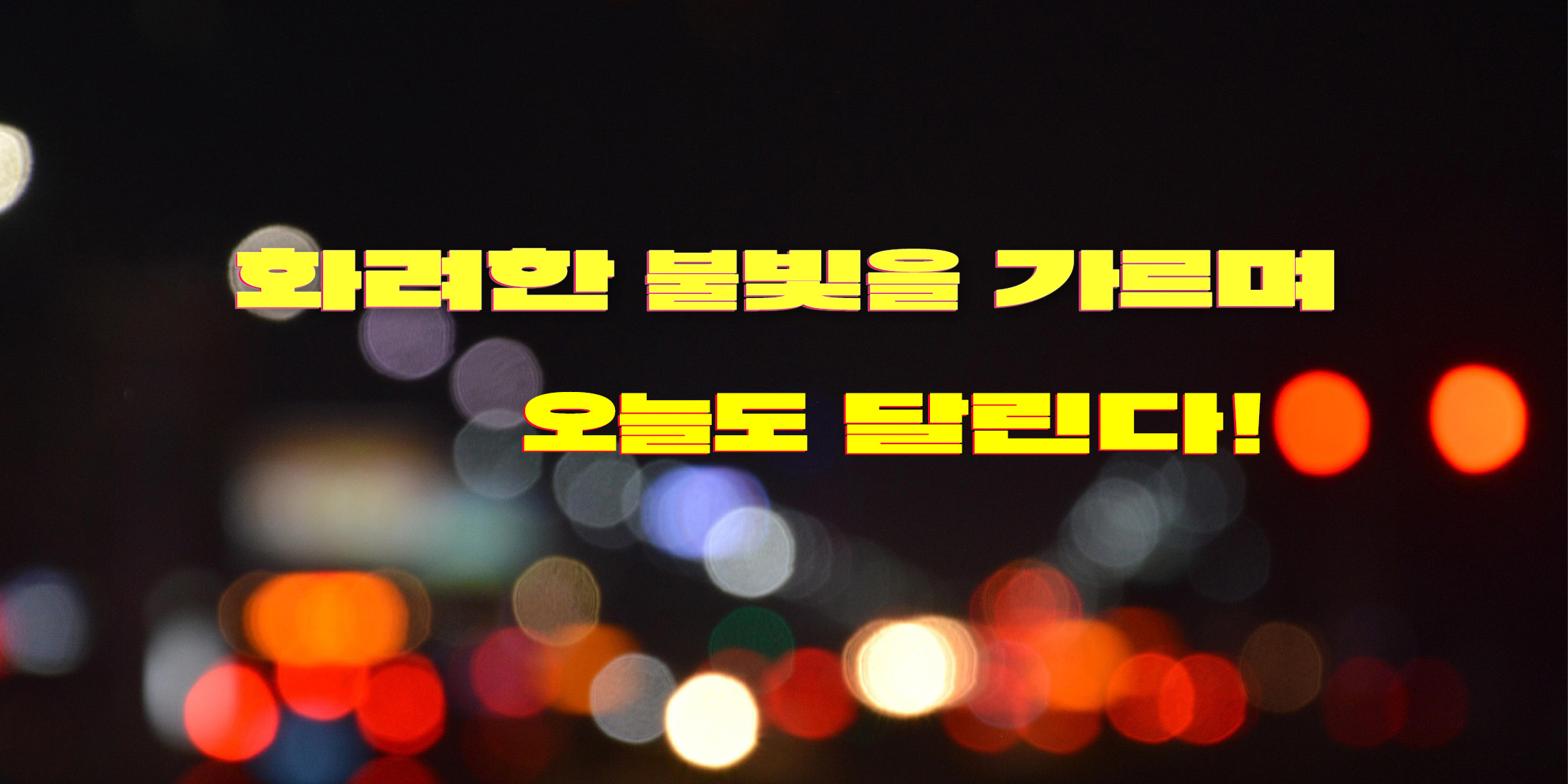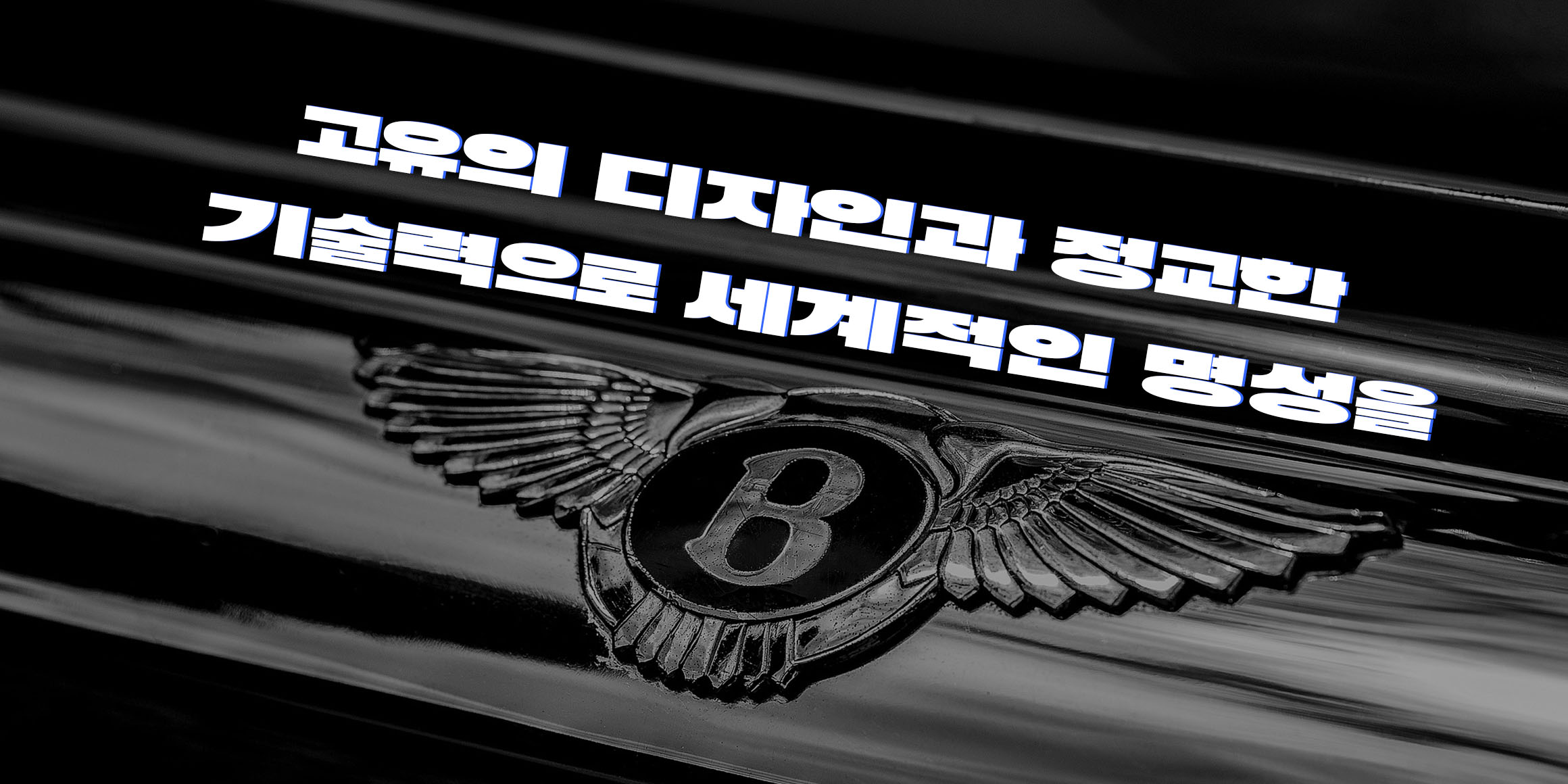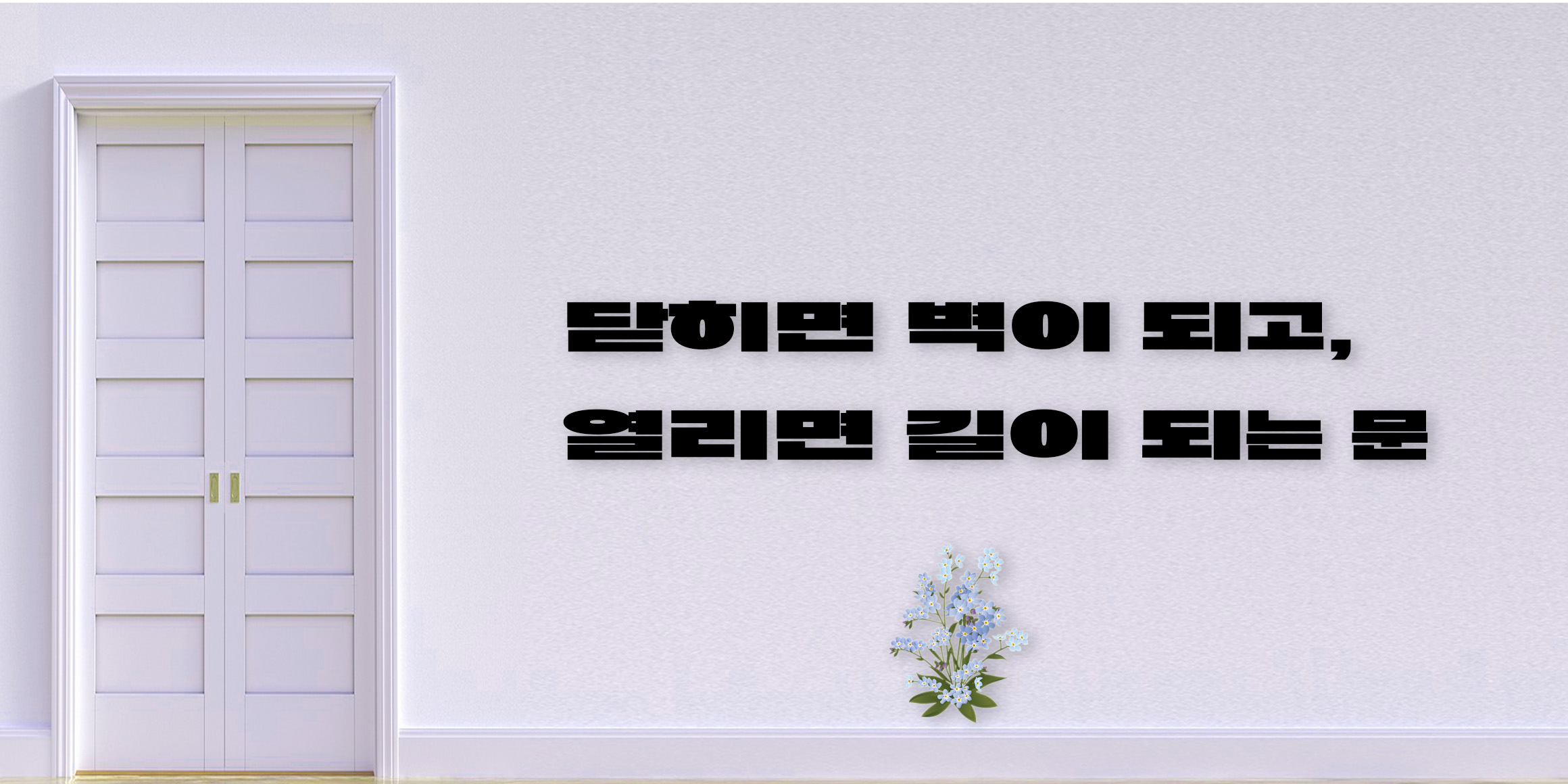
DX강남고딕와이드
DXKOREA
분류 Display,Sans,디스플레이,민부리
꽉 찬 네모꼴 구조와 묵직한 두께감이 특징인 강남고딕을
와이드한 스타일로 세로모임과 가로,섞임모임의 가로 폭을 서로 다르게 적용한
와이드 폰트이다.
압도적인 무게감으로 글꼴의 내부 속공간을 최대한 활용하여 시각적으로 매우 단단하고 강한 인상을 줍니다.
도시적 미감으로 직선의 심플함을 살려 정돈된 기계적 느낌과 함께 세련되고 스마트한 도시 분위기를 자아냅니다.
안정적인 밸런스로 가로와 세로의 획이 두껍게 꽉 들어차 있어, 짧은 문장에서도 흔들림 없는 높은 시각적 안정감을 자랑합니다.
타이틀 및 헤드라인: 임팩트가 강하고 주목도가 높아야 하는 영상 자막의 대타이틀, 유튜브 썸네일 제목 등에 적극 추천합니다.
시각 디자인 요소: 상업용 포스터, 배너 광고, 웹디자인 이미지의 메인 카피처럼 한눈에 시선을 사로잡아야 하는 곳에 적합합니다.
브랜딩: 강렬하고 현대적인 이미지를 전달하고자 하는 기업의 로고(CI/BI)나 브랜드 패키지 디자인에 유용합니다.